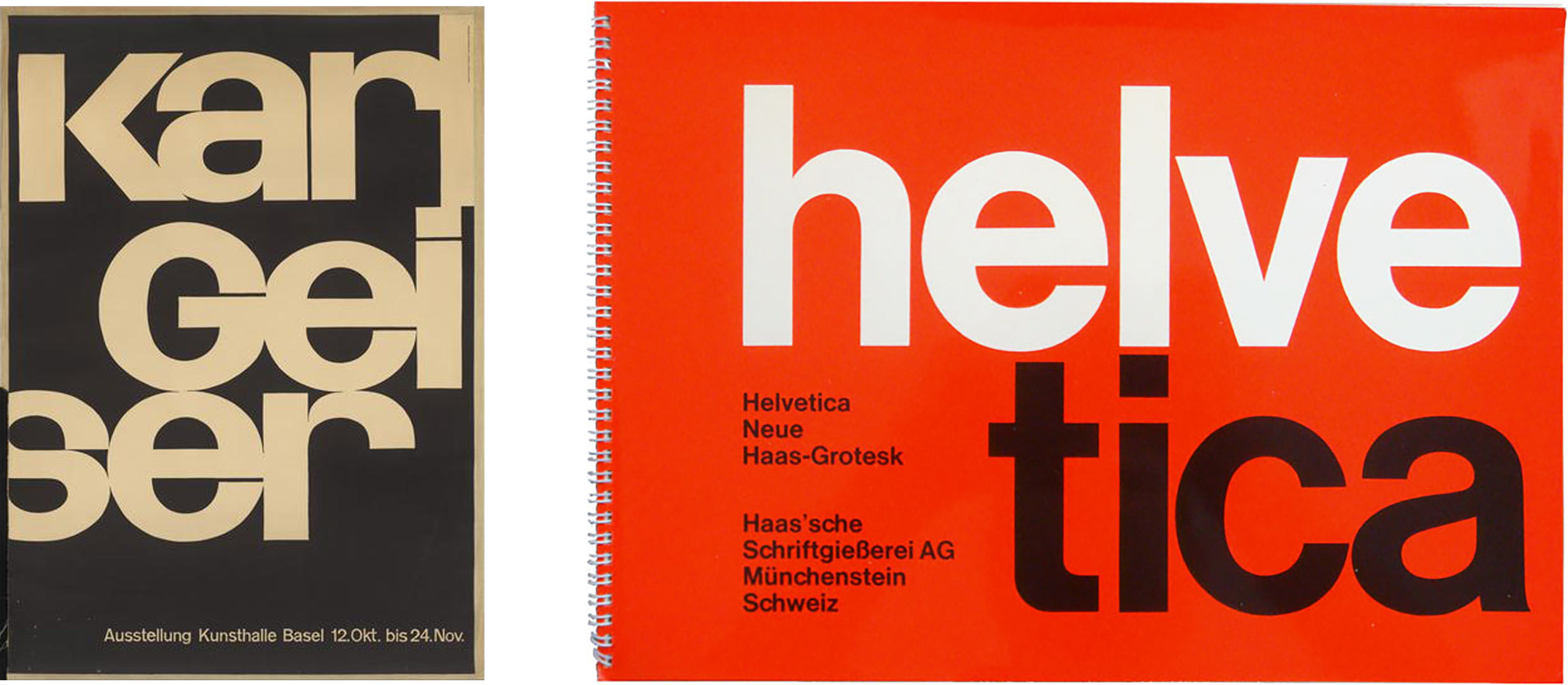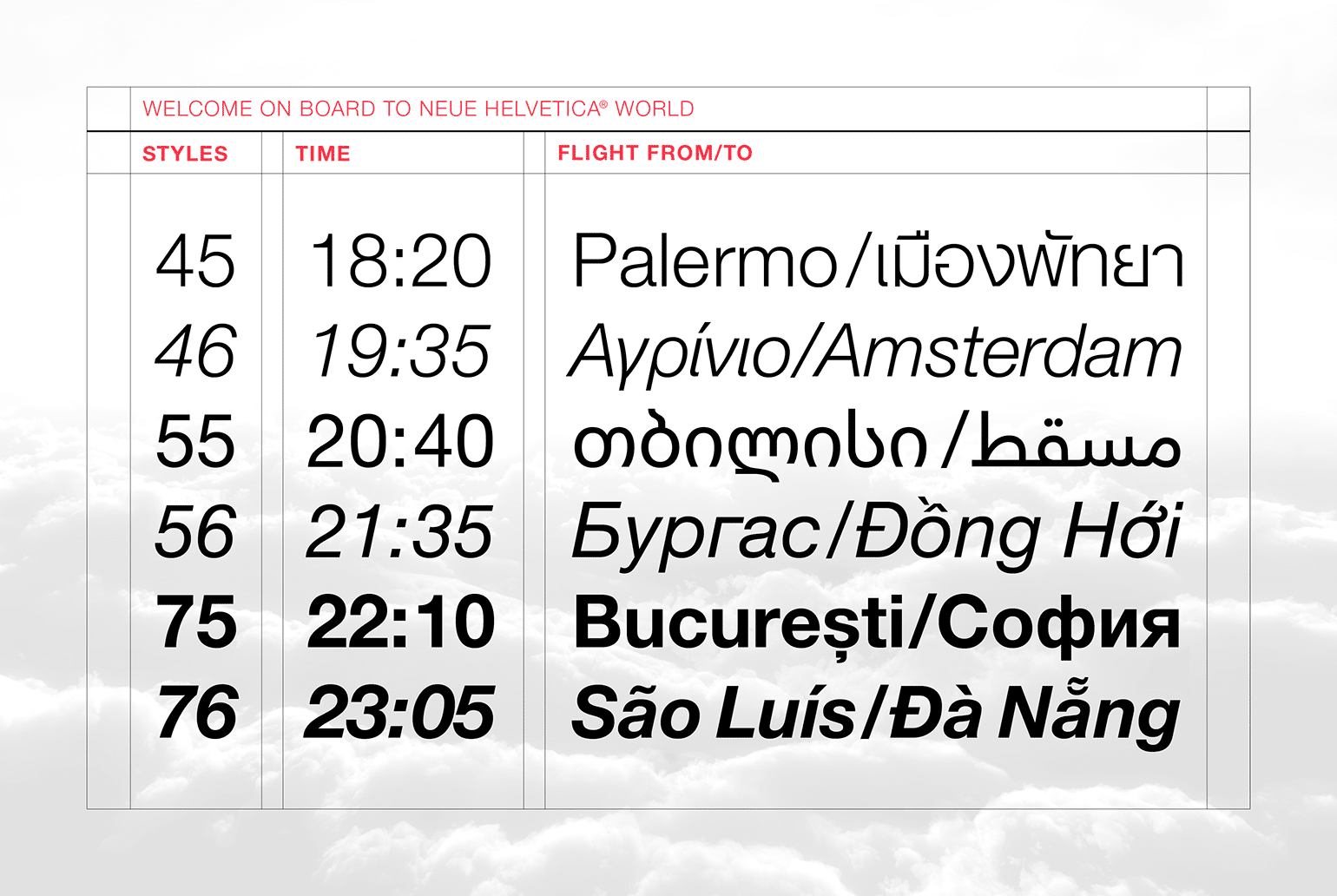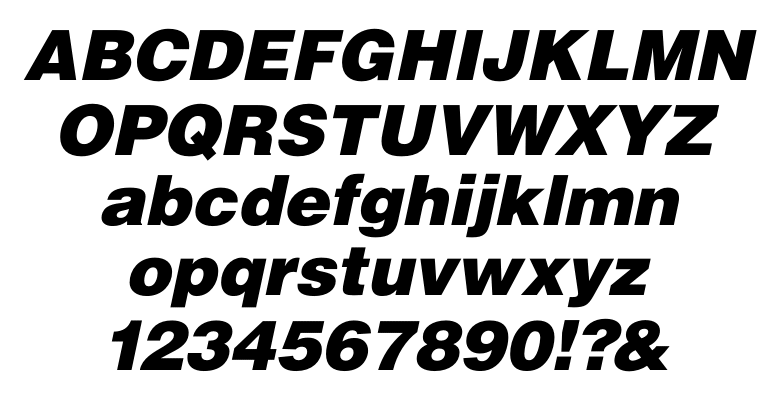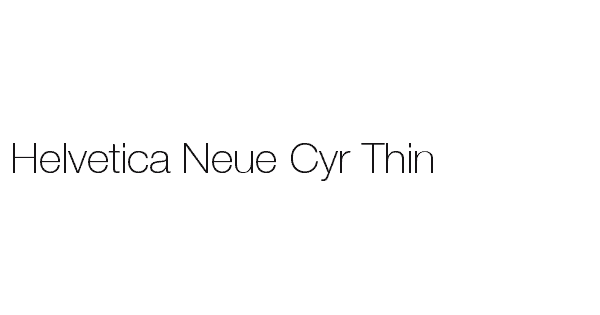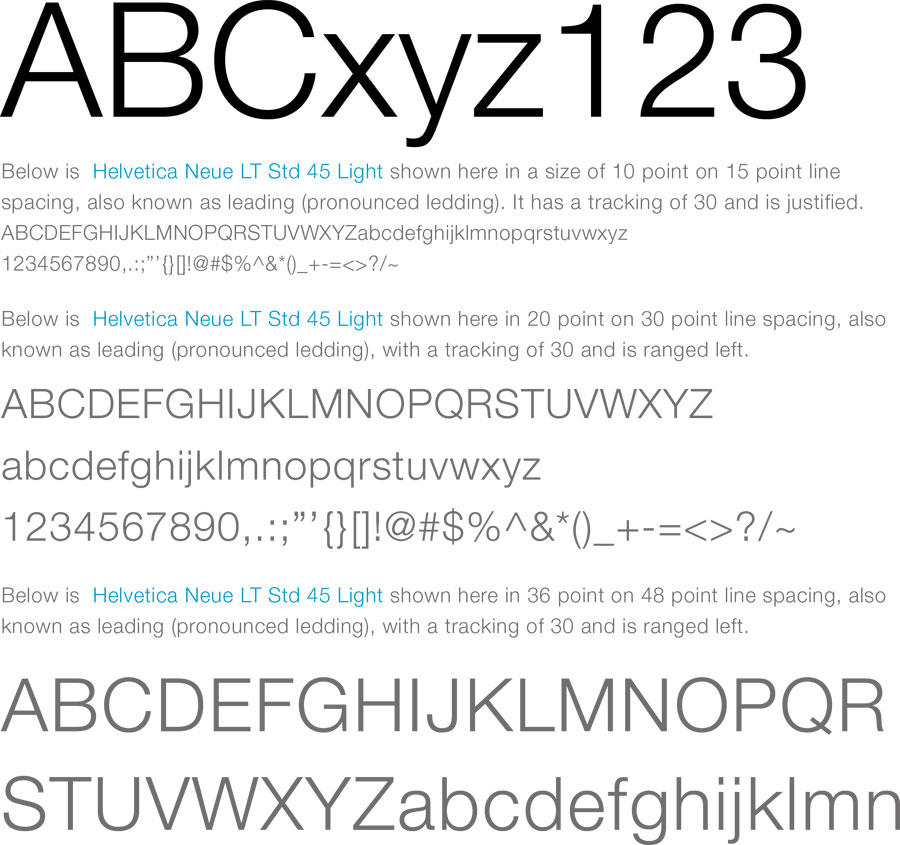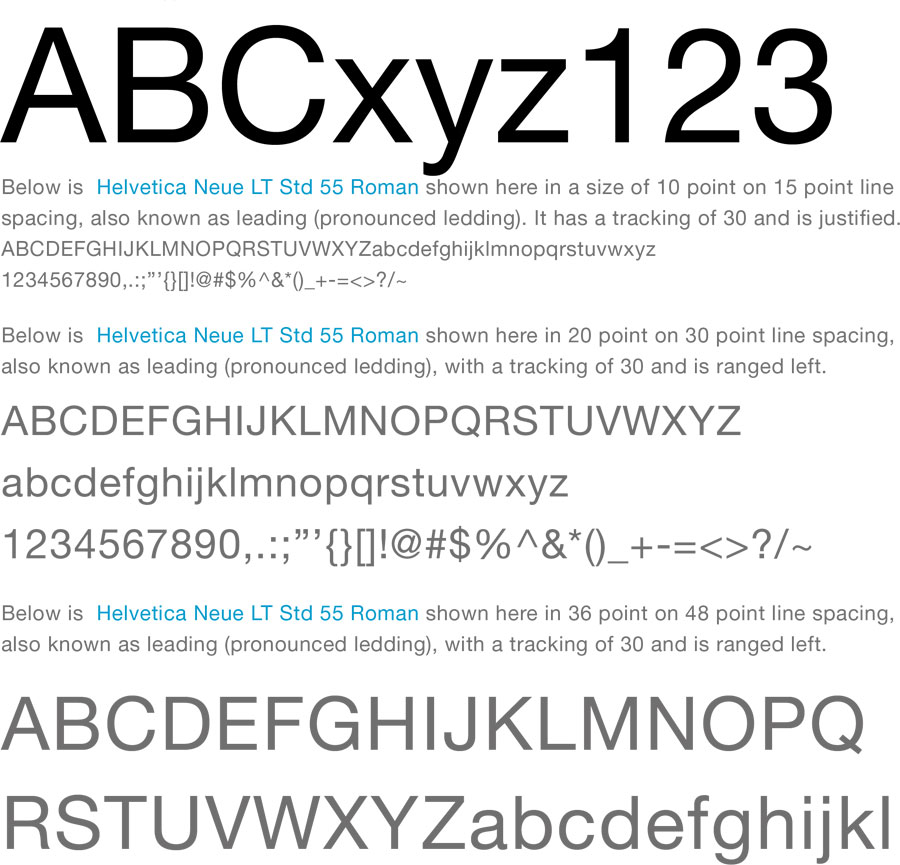
Где можно использовать Helvetica Neue?
Вы можете четко использовать шрифт на разных платформах, включая заголовки, веб-сайты, дизайн, логотипы, плакаты, баннеры, рекламу и т. Д. Он увеличивает показатель удобочитаемости и делает контекст заметным и понятным.
Helvetica Neue — это переработанный шрифт с более структурно унифицированным набором высоты и ширины.Другие изменения включают улучшенную разборчивость, более толстые знаки препинания и увеличенный интервал в числах.